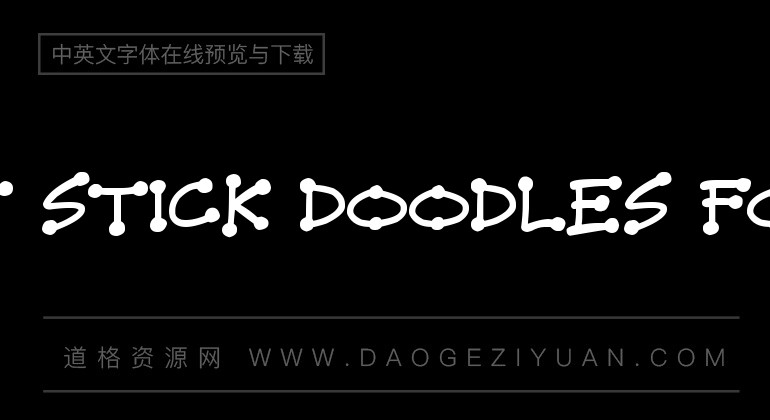
Dot Stick Doodles Font 是一种可爱的手写字体,字母被设计成由连续的小圆点和线条组成的,类似于儿童手绘的风格。这种字体的特点是简单、轻松、干净,非常适合用于卡通、儿童书籍、手工艺品等领域。 该字体包含了大写和小写字母、数字和标点符号,可与多种软件兼容,包括 Adobe Photoshop、Illustrator、InDesign 等。这使得它成为一种非常方便的字体,可以应用于许多不同的设计和创意项目中。 如果你在寻找一种富有趣味性和个性化的字体,Dot Stick Doodles Font 肯定值得一试。内容介绍
Dot Stick Doodles Font是一款非常不错的手写艺术字体,具有很好的视觉感,适合于文化类的宣传设计、商业类品牌的广告和产品包装设计以及个性化文字排版等较多场景。